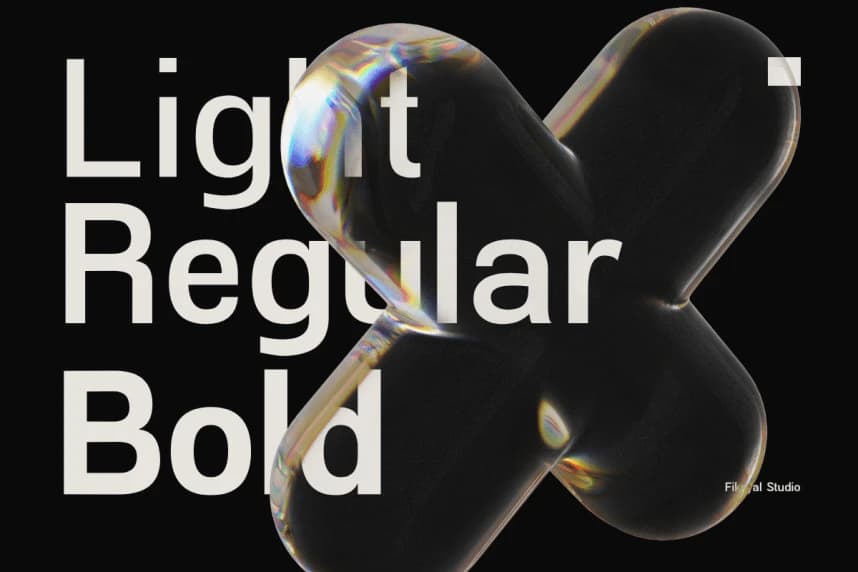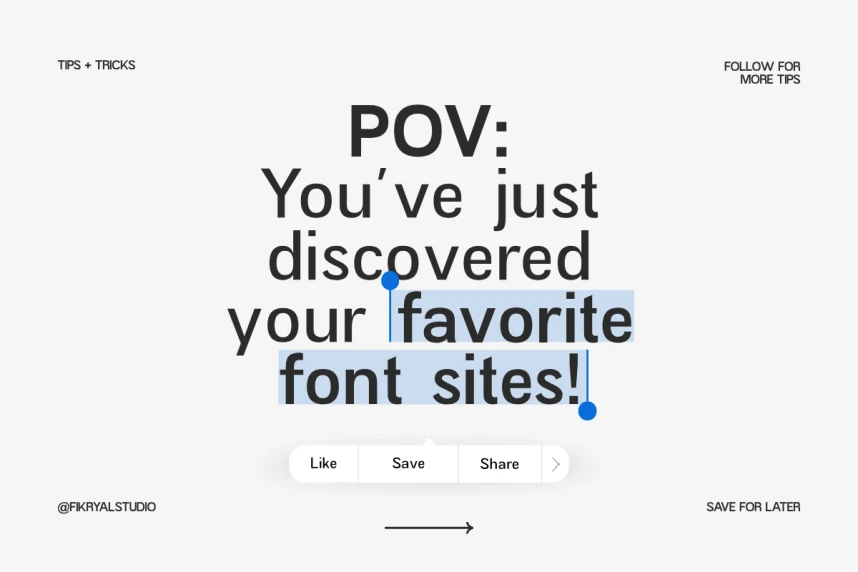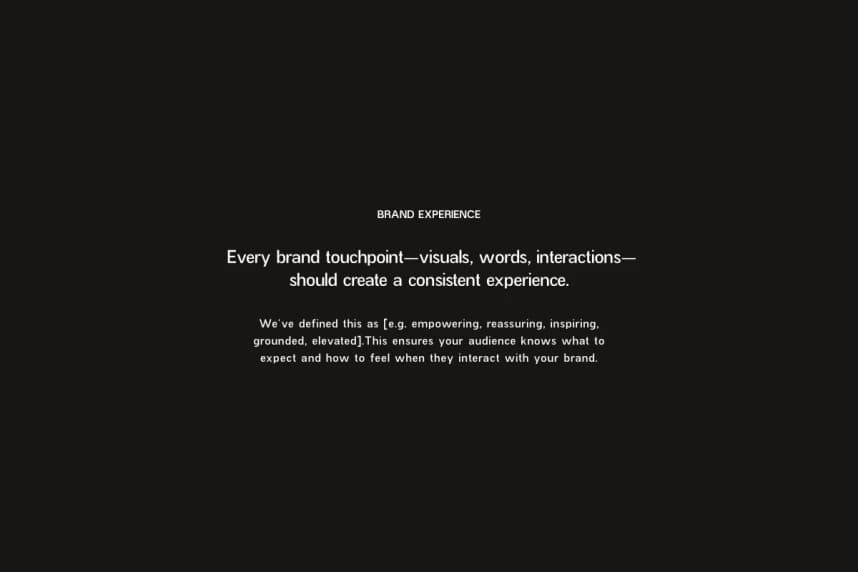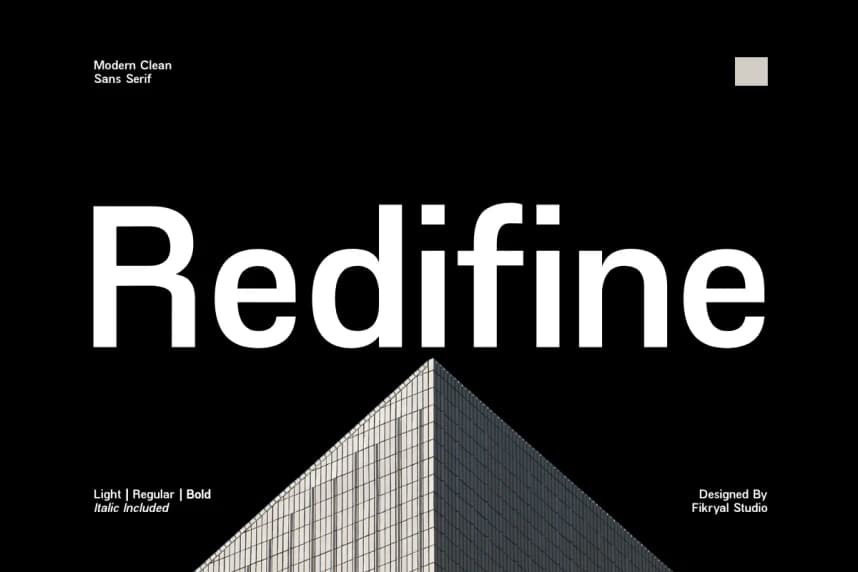
Redifine – Sans Serif Font
Redifine – Sans Serif Font, her projede netlik, zarafet ve çok yönlülük sunmak üzere tasarlanmış temiz, modern bir sans serif fontudur. Minimalist yapısı ve çağdaş hissiyle Redifine, okunabilirlikten ödün vermeden profesyonel ve cilalanmış bir görünüm isteyen tasarımcılar için mükemmeldir.
Redifine – Sans Serif Font, her proje için netlik, zarafet ve çok yönlülük sunmak üzere tasarlanmış temiz, modern bir sans serif yazı tipidir. Minimalist yapısı ve çağdaş hissiyle Redifine, okunabilirlikten ödün vermeden profesyonel ve cilalı bir görünüm isteyen tasarımcılar için mükemmeldir.